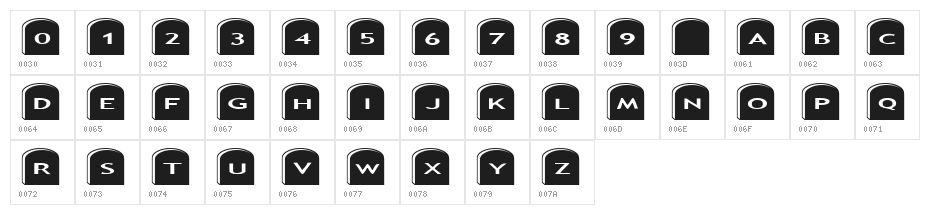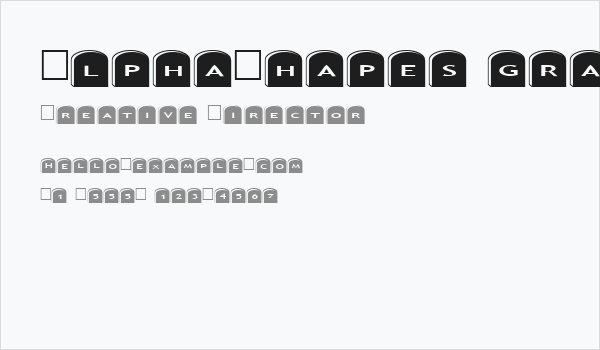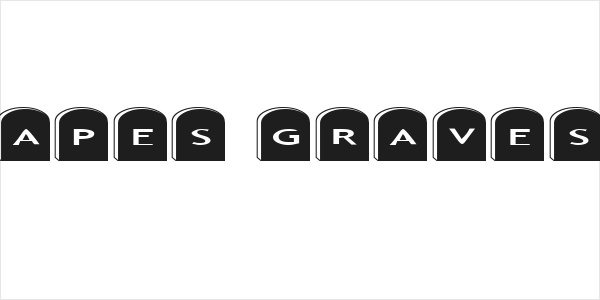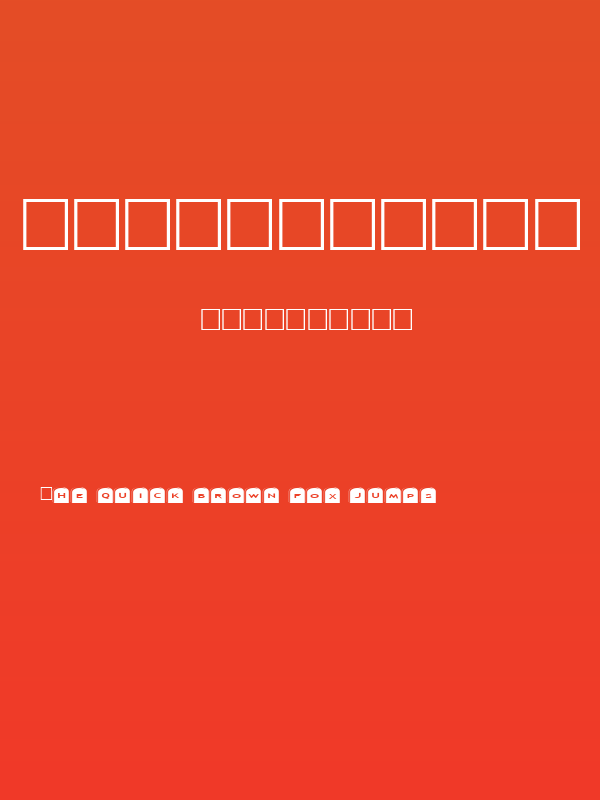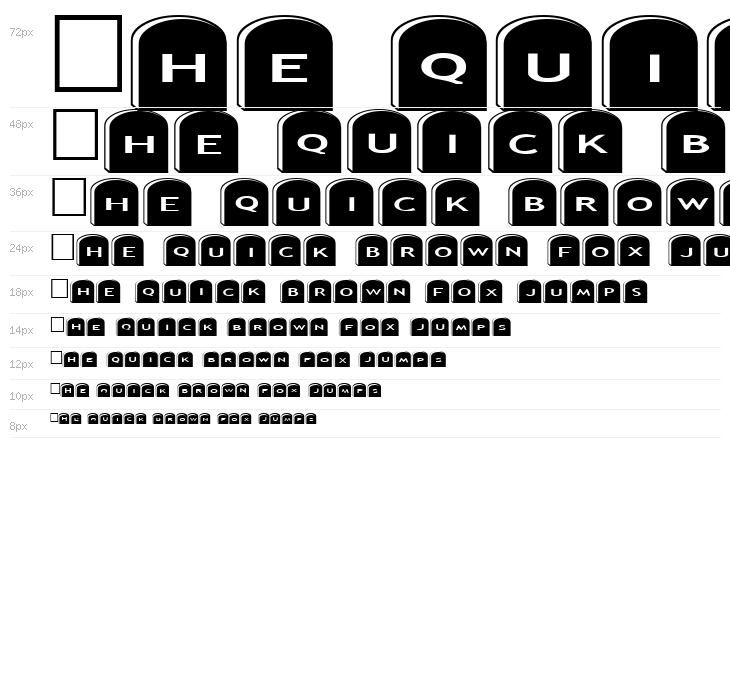
AlphaShapes gravestones 2 Font
| Progetti proposti | Ideal for Halloween invitations, themed posters, horror movie titles, or any project needing a spooky aesthetic. |